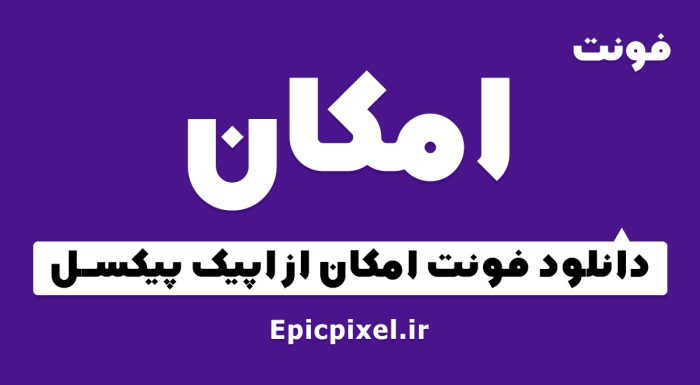
فونت امکان یک انتخاب عالی برای کسانی است که به دنبال فونتی مدرن، خوانا و چندمنظوره برای پروژه های فارسی خود هستند. این فونت با طراحی ساده و در عین حال جذاب خود، می تواند جلوه ای خاص به نوشته های شما ببخشد.
یکی از ویژگی های برجستهٔ «امکان»، گستردگی وزن های آن است؛ از نسخه های بسیار نازک گرفته تا وزن های ضخیم و سنگین، که این تنوع به شما اجازه می دهد در موقعیت های مختلف، از عناوین گرفته تا متن های طولانی، به راحتی از آن استفاده کنید. طراحی این فونت به گونه ای است که در اندازه های مختلف، چه در چاپ و چه در صفحات وب، خوانایی خود را حفظ می کند. این ویژگی به خصوص برای طراحانی که با رسانه های مختلف سروکار دارند، بسیار مهم است.
فونت امکان با وجود سادگی، دارای ظرافت های خاصی در طراحی حروف است که آن را از سایر فونت های مشابه متمایز می کند. این ظرافت ها در جزئیات حروف دیده می شوند و به متن شما شخصیتی منحصربه فرد می بخشند. البته باید به این نکته هم اشاره کرد که این فونت، شاید برای پروژه های بسیار سنتی یا کلاسیک، انتخاب ایده آلی نباشد؛ چرا که تمرکز آن بیشتر بر مدرنیته و سادگی است.
اگر به دنبال فونتی هستید که هم در طراحی های چاپی و هم در طراحی وب، جلوه ای زیبا و حرفه ای به کار شما ببخشد، «امکان» گزینه ای بسیار مناسب است. این فونت با ارائهٔ ترکیبی از سادگی، خوانایی و زیبایی، می تواند نیازهای گوناگون شما را برطرف کند.